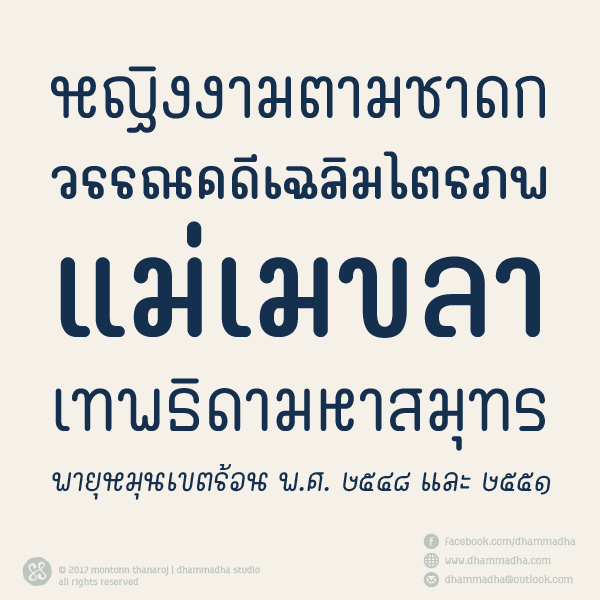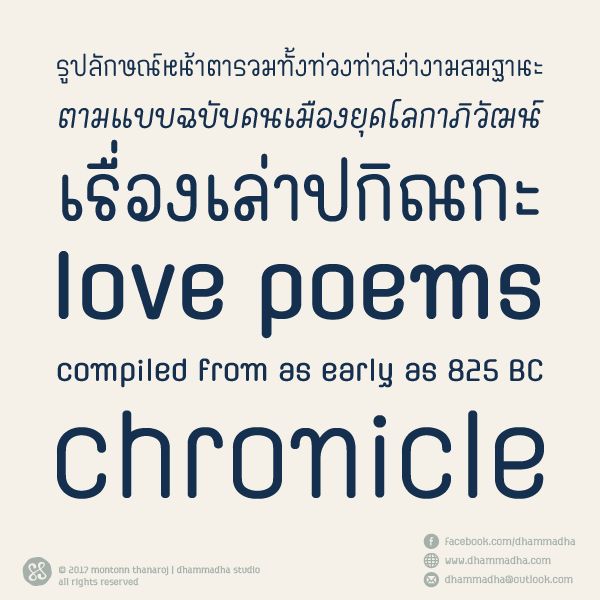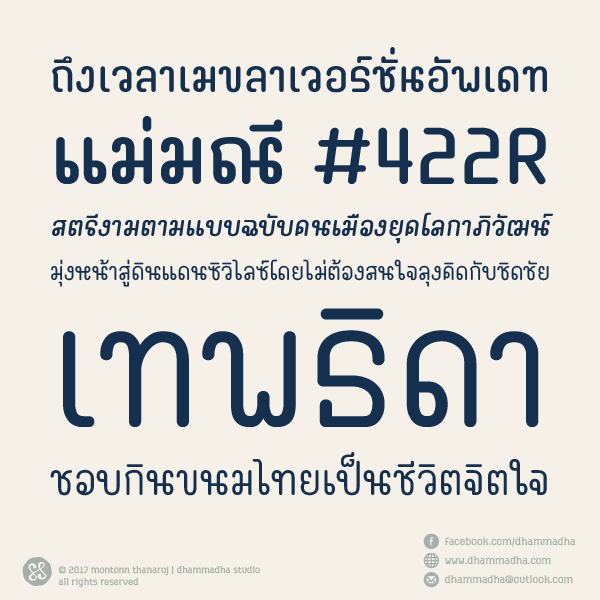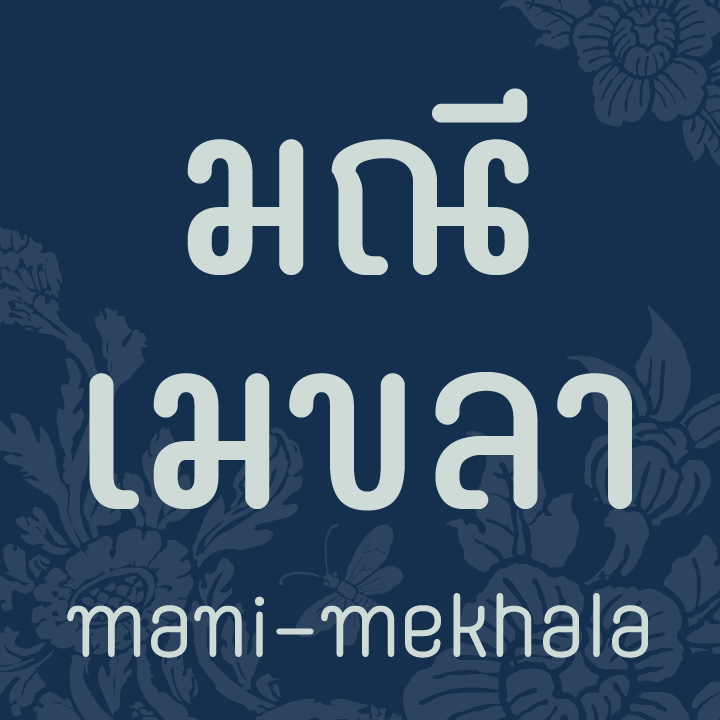
มณี-เมขลา | mani-mekhala
ชุดอักษร “มณี-เมขลา” ชุดนี้ร่างลงกระดาษไว้นานประมาณหนึ่ง
สักประมาณ 3-4 ปี เห็นจะได้
ที่เริ่มต้นอย่างนี้ ไม่ใช่อะไรหรอกฮะ
คือจะบอกว่า ค้นที่มาที่ไปของชุดอักษรนี้ไม่เจอ T_T
เพราะฉะนั้น เราจะข้ามส่วนนี้ไปฮะ
ชุดอักษรประกอบด้วยฟอนต์ 4 น้ำหนัก พร้อมตัวเอียง
mani-mekhala สามารถใช้งานภาษาไทยได้อย่างสมบูรณ์ ฟีเจอร์ใช้งานครอบคลุม
(OpenType / Ligature / Small Caps)